什么字体设计师最常使用?什么字体最受商业用途欢迎?这两个问题小编搜集了许多答案,在设计师中呼声最高的定当行书字体莫属了,行书是一种书法的统称,分为行楷和行草两种。行楷实用性高、方正得体,行草艺术性极高、浑厚洒脱。下面给大家介绍三款下载率超高的商业使用行书字体,请看下面的图片字体。
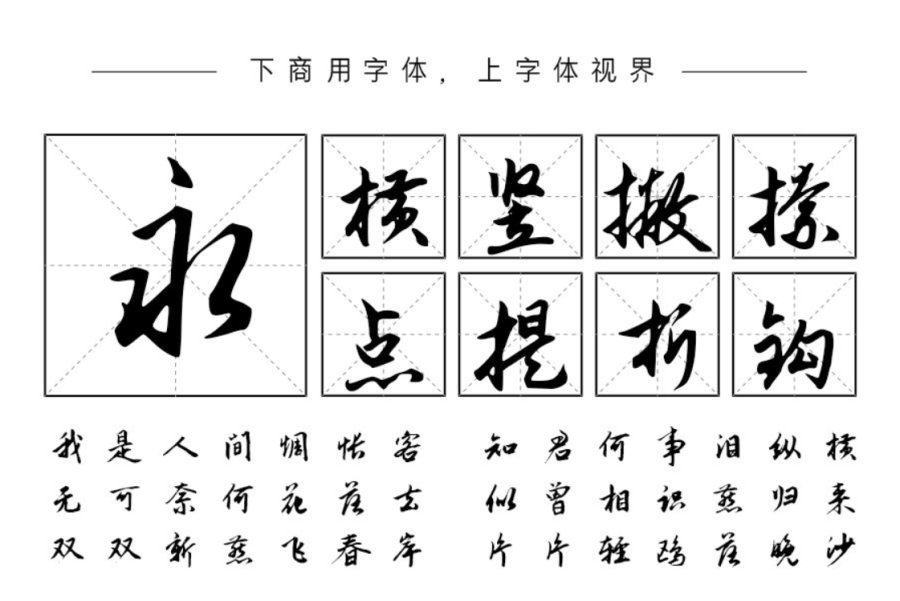
“钟齐志莽行书”这款字体是一款非常有艺术特色的书法字体,这款字体字形潇洒飘逸,形体端秀而骨架劲挺,整体效果非常出色,非常适用于广告设计、艺术设计、书法练习等其它商业用途设计。
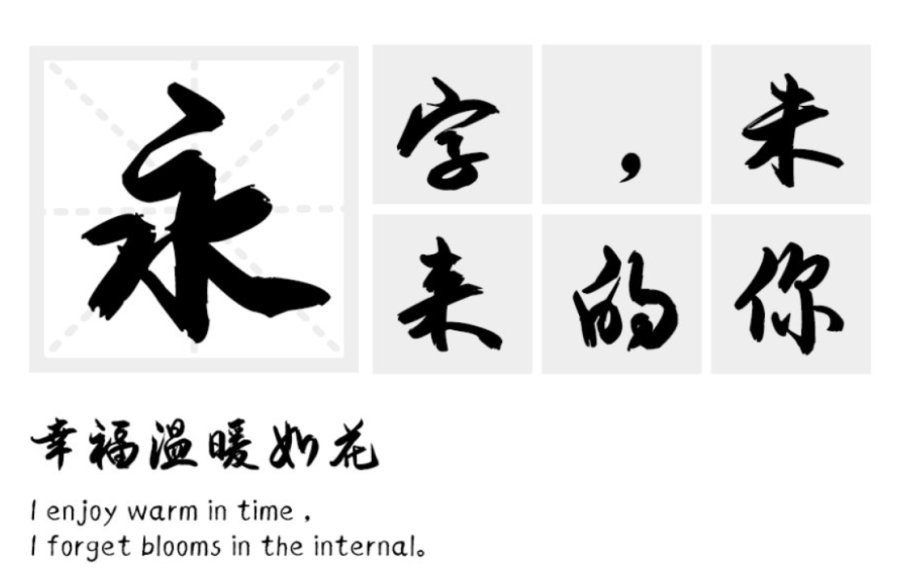
这款字体叫做“安景臣毛笔行书”,该毛笔书写的行书既有深厚的传统功力,又融入的现代人的审美气息,作者在创作时力求规范平和,易于识别。字型规范而不失特色。严谨秀美透出从容和优雅,让人赏心悦目,百看不厌深受设计师的喜爱。
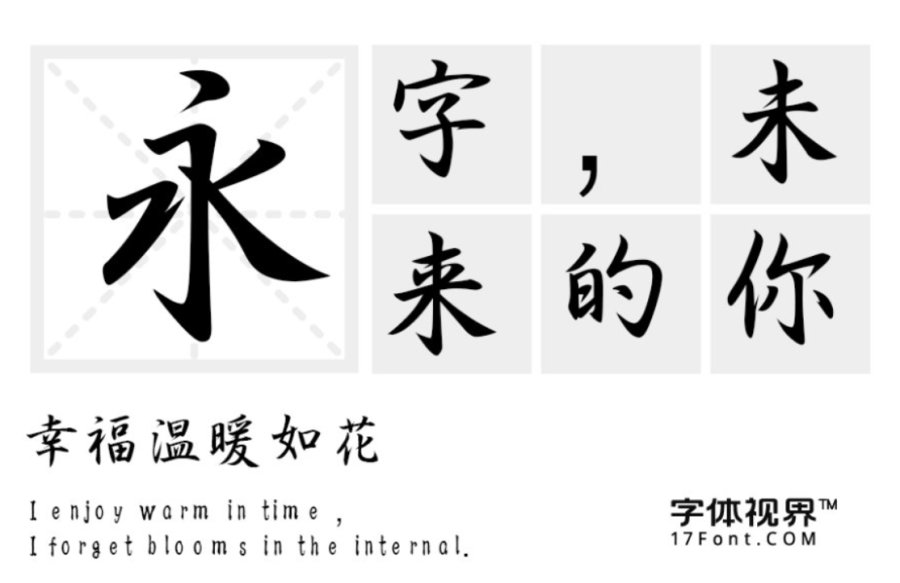
这款“三极行书简体”结构紧凑,笔画写意,笔意连接张弛有度,遒劲有力。本作品适用于印刷媒介的标题与正文排版、各类屏幕显示及影视字幕、游戏等商业用途设计。
有书法味道的行书,是追求中国风与商务正式感的一种折中风格。不仅适用于现代感的设计风格还适合许多特色风格设计。以上三款字体对您的疑问有帮助的话,保存喜欢的字体图片,点击识别字体了解字体信息,下载这些在设计师中下载率超高的字体吧!